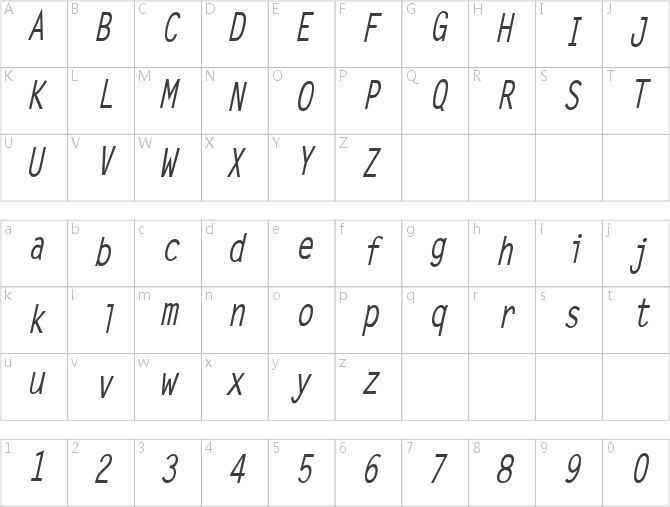
字體名稱: Lechter
Lechter-Condensed-Bold-Italic
Lechter-Condensed-Bold-Italic字體字庫是一款讓人賞心悅目、百看不厭的英文字體,適合各類廣告和產品包裝設計應用,字體大小0.04MB,格式為ttf字體,上傳用戶是漫步云端,作者/版權方為未知